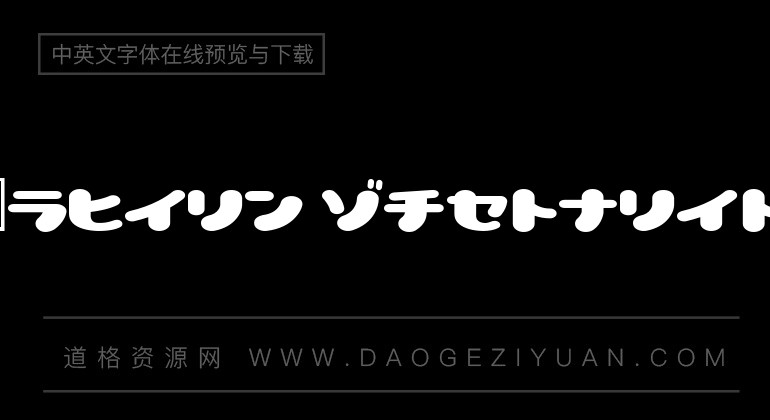
Lovely Capsules 是一種漂亮的手寫風格字體,它的特點是字母形狀簡潔,線條柔和,整體呈現出一種溫馨,親切的感覺。該字體適用於各種設計風格,包括卡通、插畫、手工製品等等,因為它能夠為這些設計帶來一種溫暖、輕鬆、自然的氛圍。此外,該字體也非常適合用於個人博客、DIY製品、婚禮請柬等場合,因為它能夠為這些活動帶來一種別緻、浪漫的氣息。內容介紹
Lovely Capsules是一款非常不錯的手寫藝術字體,具有很好的視覺感,適合於文化類的宣傳設計、商業類品牌的廣告和產品包裝設計以及個性化文字排版等較多場景。